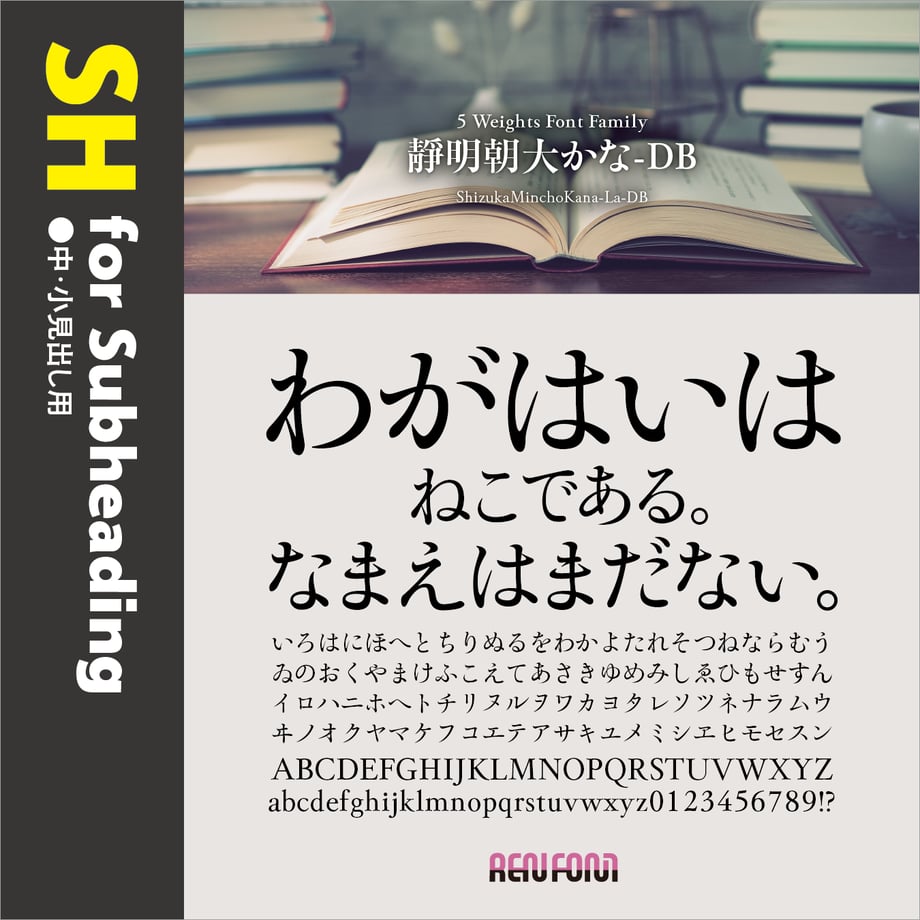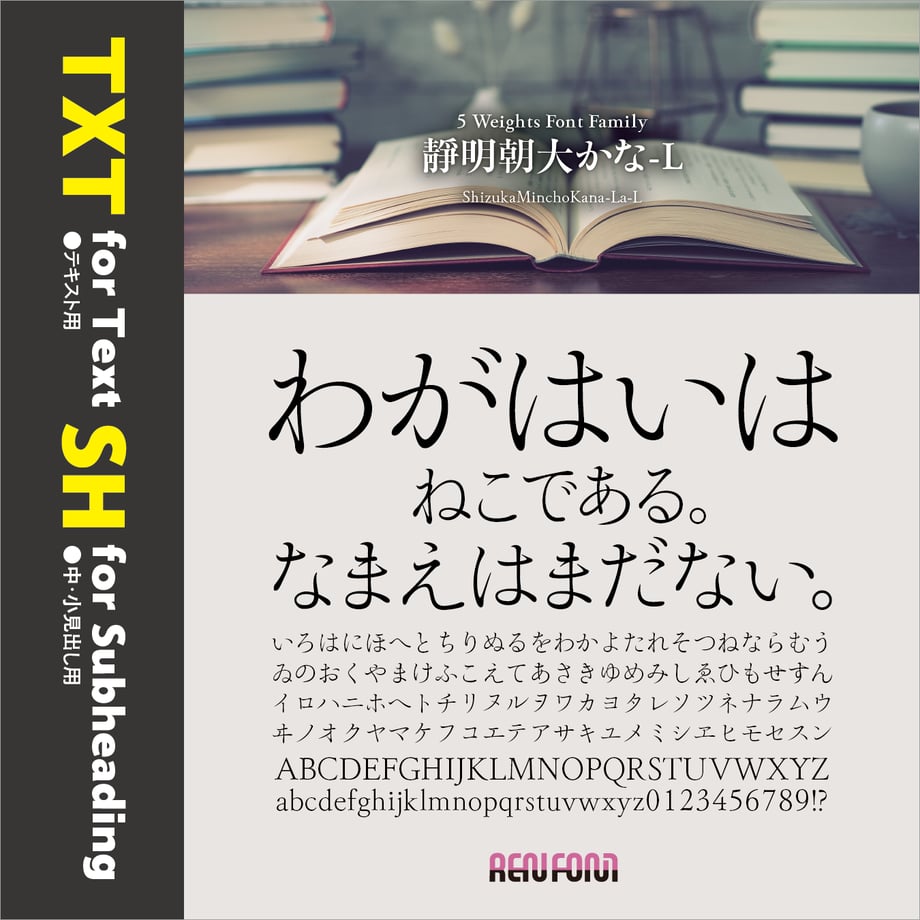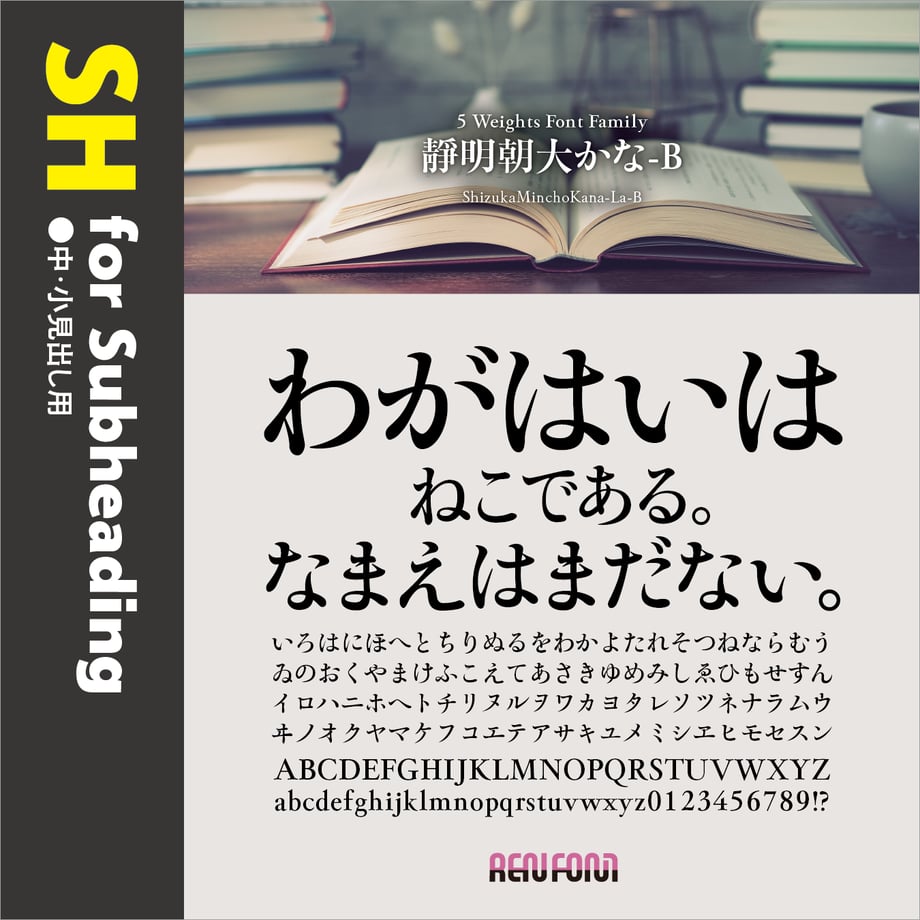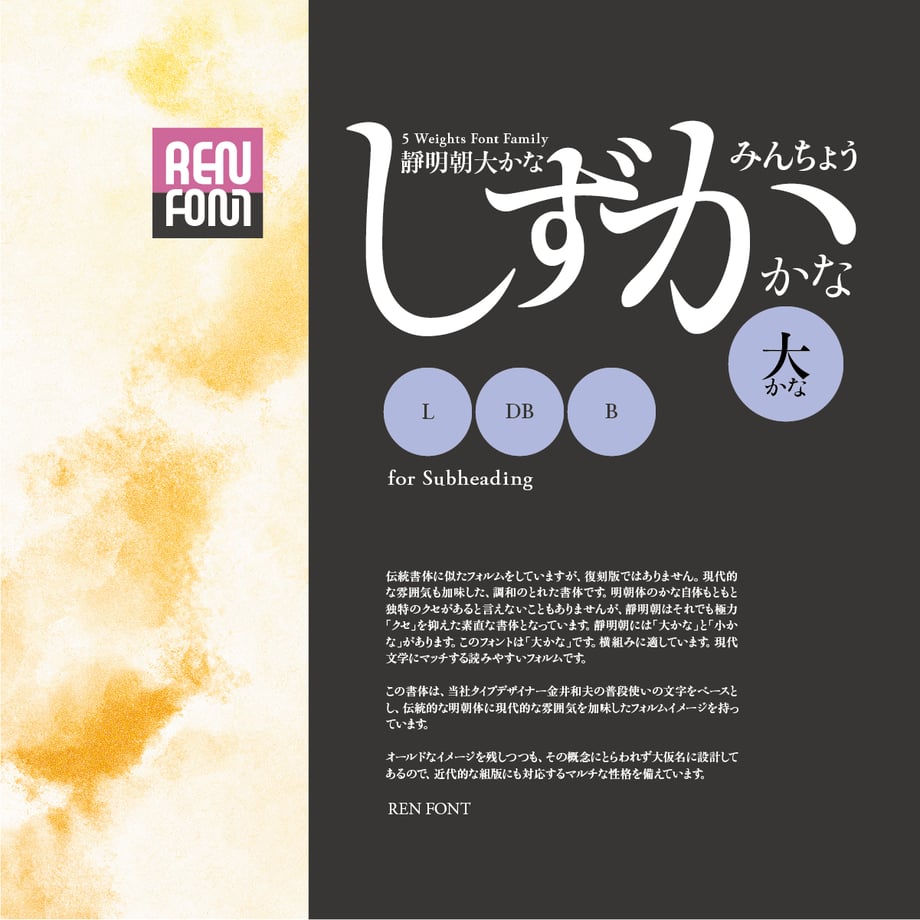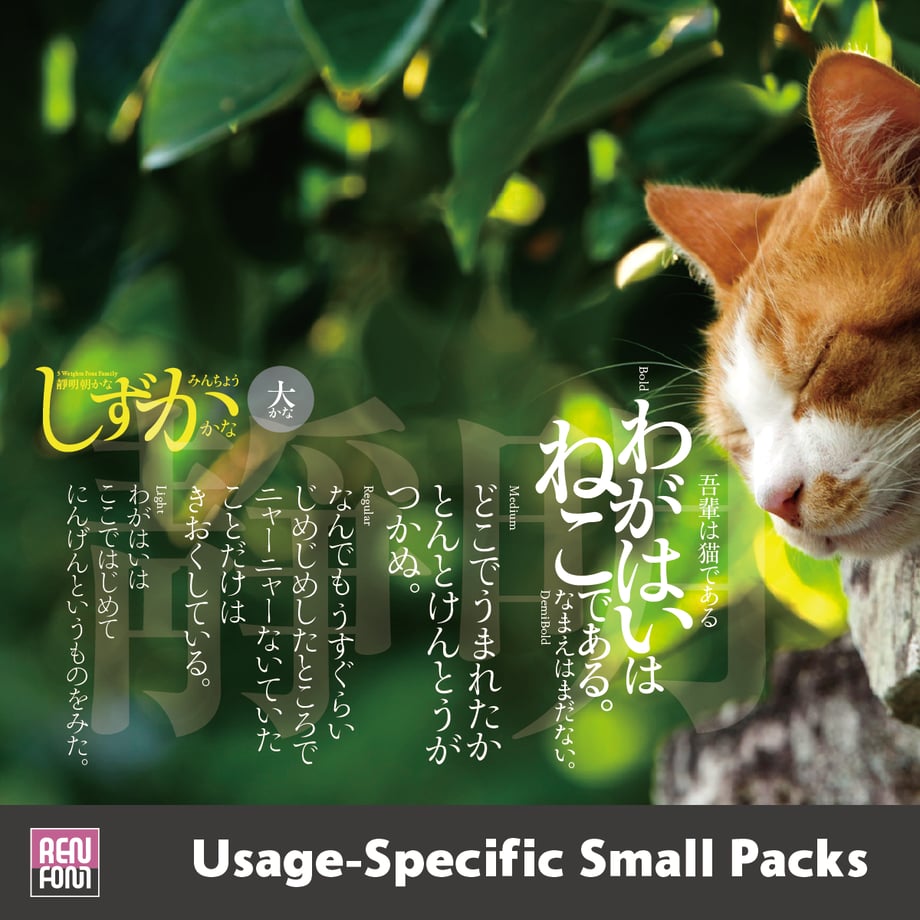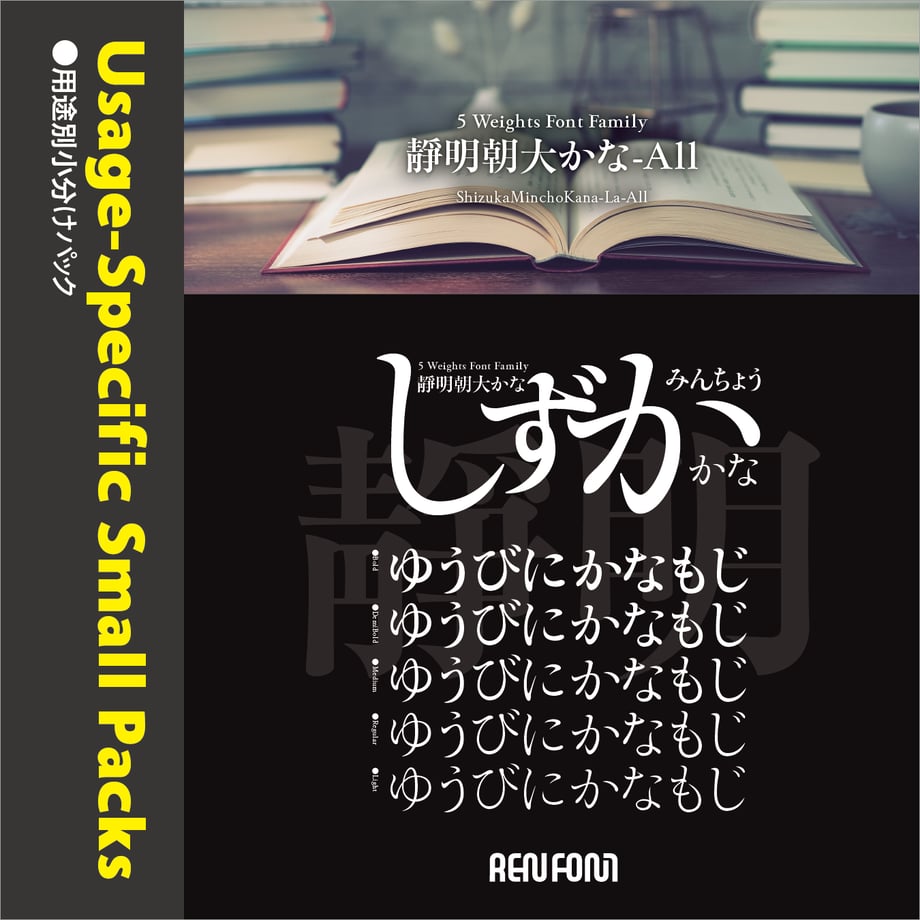
靜明朝大かな-SH(中・小見出し用)L/DB/B
読みやすさにこだわった
靜明朝大かな 5ウェイトファミリー / OpenType
小説などの長文に適した素直なフォルム
伝統書体に似たフォルムをしていますが、復刻版ではありません。現代的な雰囲気も加味した、調和のとれた書体です。明朝体のかな自体もともと独特のクセがあると言えないこともありませんが、靜明朝はそれでも極力「クセ」を抑えた素直な書体となっています。靜明朝には「大かな」と「小かな」があります。このフォントは「大かな」です。横組みに適しています。現代文学にマッチする読みやすいフォルムです。
この書体は、当社タイプデザイナー金井和夫の普段使いの文字をベースとし、伝統的な明朝体に現代的な雰囲気を加味したフォルムイメージを持っています。「L(ライト)」、「R(レギュラー)」、「M(ミディアム)」、「DB(デミボールド)」、「B(ボールド)」の、合計5ウェイトで構成されています。
また、オールドなイメージを残しつつも、その概念にとらわれず大仮名に設計してあるので、近代的な組版にも対応するマルチな性格を備えています。
横組みに適している理由とは
現代は、すっかり横組みの文化。英文との混植が増えたこともあり、機能性を重視してほとんどの書類は横組みになっています。しかし、かなは本来縦組みに適した作りになっています。それを横組みすると、さまざま問題がおきます。横幅が狭い文字種が多いからです。ベタ組みすると文字間が広く開いてしまう箇所が多くなり、大変読みにくくなります。私たちは実は「習慣」のもとに、普段から読みにくい文章を読まされているのです。
靜明朝大かなは、横幅が狭い文字種を心持ち広く、そして、全体を大きめに設計しました。こうすることで文字間のばらつきが緩和され、横組みの文章も読みやすくなります。
他社「総合書体」との「共存」
現在、世の中に出回っているフォントの数はすでに数え切れないほどになっています。明朝体に限ってもまた然り。
靜明朝かなは5ウェイトありますが、それぞれの太さにさほどの差がありません。本来は3ウェイト展開にすべきかも知れませんが、あえて5ウェイトにしたのにはそれなりの理由があります。
かなフォントは、単独ではあまり存在意義はありません。漢字と組み合わせてはじめて「意味」が生じます。
フォントのウェイト呼称は、ほとんどのベンダが「ライト」から「ウルトラ」に至る7から9ウェイト展開をしています。ただ、それぞれの太さに明確な基準はなく、各ベンダの判断によります。ですので、例えば「ライト」でも太さが微妙に異なってきます。かなフォントがそれに対応するには、細かいウェイト展開が必要となります。
当社かなフォントの細かいウェイト展開は、それが理由です。お好みに合わせて合成フォントをお楽しみいただければ幸いです。
日本語文章の約70%はひらがな、カタカナが占めているといわれます。それだけに紙面の雰囲気を左右し、決定づける重要なアイテムです。図は、モリサワのリュウミンと靜明朝を並べて比較したもの。同じ文字種でもこれだけ印象が違います。
靜明朝大かなは、長文を組むために開発、読みやすさを重視しクセを極力なくしたフォルムになっており、特に横組みに適しています。そのフォルムは、のびやかでなめらか。先端はすべて丸く処理しました。また、「か・な・ね」などの収筆は跳ねずに止めてあります。一文字ひともじの独立性を大切にしました。
伝統書体を踏襲したフォルムですが、復刻版ではなく、現代にマッチするシャープな雰囲気も同時に持たせました。
欧文・数字は、奔放な両かなとは異なり、クセの少ない伝統的なイメージにデザインしました。わずかに「K」「Q」「R」のテールに「かな」の雰囲気を持たせてあります。
格調高いGaramond調の形状ですが、若干現代風な設計になっています。欧文書体としての単独使用にも十分に耐えうる、和文付嘱書体としては稀な、非常に高い完成度を持っています。